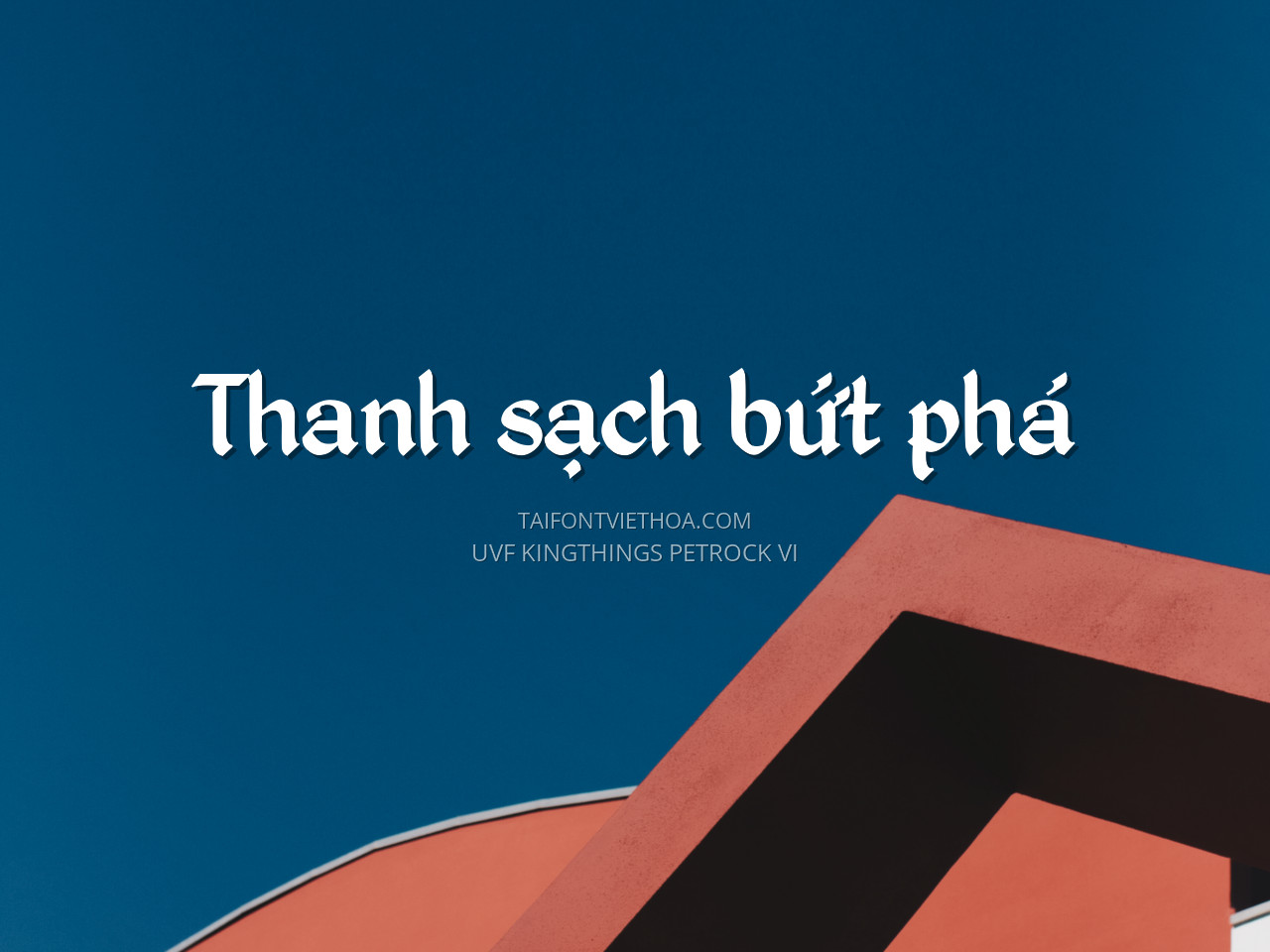
Font việt hóa Kingthings Petrock Vi
Giới thiệu về font Kingthings Petrock Vi
Kingthings Petrock Vi là một font chữ mang phong cách Gothic cổ điển, lấy cảm hứng từ những bản viết tay thời Trung cổ và các bản thảo chạm khắc trên đá. Font được thiết kế bởi Kevin King – một nhà thiết kế người Anh nổi tiếng với các bộ font mang hơi hướng lịch sử và thủ công. Phiên bản Việt hóa này đã được sưu tầm và chia sẻ bởi thành viên Font Chuẩn, đồng thời được taifontviethoa.com tích hợp vào các dự án có yếu tố cổ điển, fantasy, hoặc mang màu sắc huyền thoại – lịch sử.
Đặc điểm thiết kế và ứng dụng của Kingthings Petrock Vi
Kingthings Petrock Vi sở hữu các ký tự uốn lượn, thanh mảnh nhưng phức tạp, với các chi tiết đậm chất Gothic như đầu nét nhọn, chân móc, và sự đối xứng mang tính nghệ thuật cao. Font phù hợp khi cần tạo ra cảm giác cổ trang, bí ẩn hoặc trang trọng. Với khả năng hỗ trợ tiếng Việt đầy đủ, font dễ dàng ứng dụng trong các ấn phẩm truyền thông nghệ thuật, sự kiện văn hóa hoặc thiết kế dành cho game, phim ảnh.
Ứng dụng lý tưởng: tiêu đề game fantasy, poster phim lịch sử, bìa sách huyền bí, sản phẩm thủ công mỹ nghệ hoặc lễ hội cổ truyền. Ngành nghề phù hợp: văn hóa – nghệ thuật, sự kiện truyền thống, phim ảnh, thiết kế game và truyền thông sáng tạo.